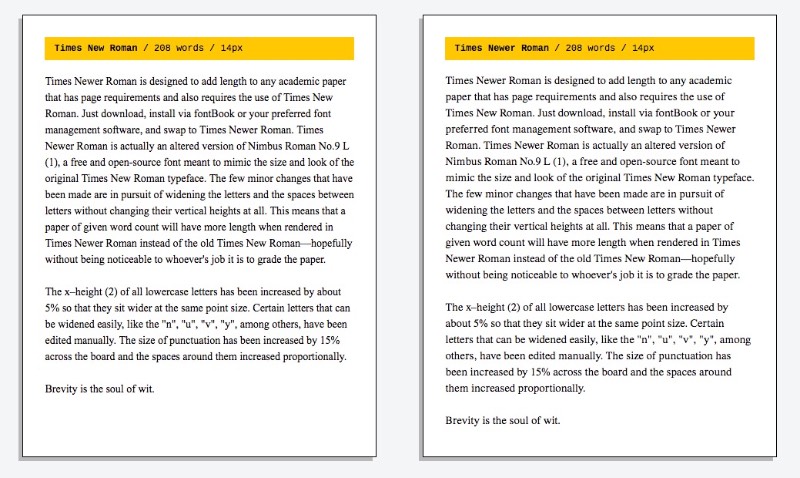
Times Newer Roman: Uma Fonte feita para parecer que você escreveu muito
Escrever suas ideias é mais complicado do que muita gente pensa. Acredito que pode ser ainda mais complicado quando se trata de textos acadêmicos e tudo aquilo que precisamos escrever na escola e na faculdade. Acredito que foi pensando nisso que surgiu a Times Newer Roman.
A Times Newer Roman surgiu para criar a ilusão de que o texto que você escreveu é mais longo do que ele é. Você não vai ter que improvisar pontuações maiores que o normal, margens que vem com mais espaços e qualquer outra gambiarra que você tenha pensado. Essa fonte é a solução dos seus problemas por alguns motivos bem simples.
Primeiro, porque ela é quase igual a Times New Roman que é a fonte clássica de quase todos trabalhos acadêmicos hoje em dia. Segundo, porque ela é de 5 a 10% mais larga do que a Times New Roman. Isso deixa essa fonte com um visual sutilmente maior do que o esperado mas, sem a comparação direta com a fonte certa, fica praticamente impossível distinguir uma da outra.
De acordo com o site dessa fonte, se você escrever um texto de 15 páginas, usando de texto em 12 pts e com espaçamento simples, você vai precisar de cerca de 6.680 palavras usando da Times New Roman. Se você quiser ocupar as mesmas 15 páginas com a Times Newer Roman, você vai precisar de cerca de 5.800 palavras.
Tecnicamente falando, essa fonte não é uma cópia alterada da Times New Roman. Sendo que essa última é uma fonte licenciada, o que aconteceu foi que os designers responsáveis foram para a Nimbus Roman No. L, que é uma fonte gratuita e open source. O trabalho aqui foi de aumentar o espaçamento entre os caracteres e pronto.